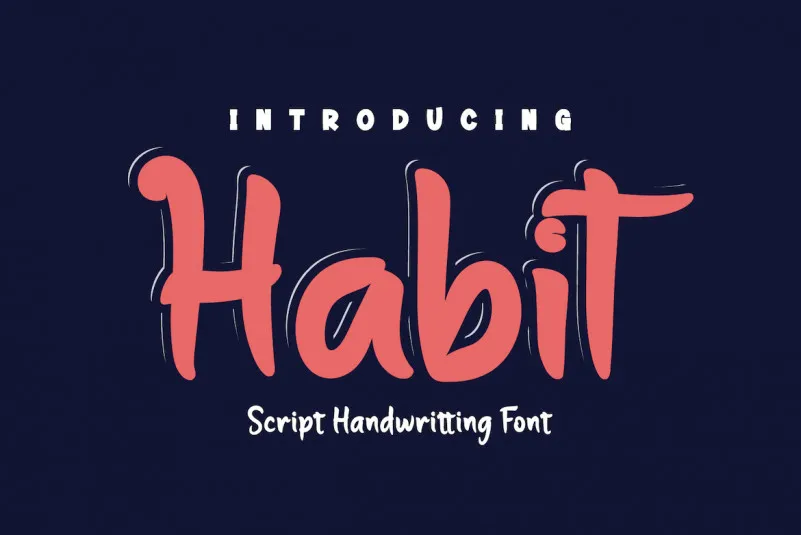
Habit Font é uma tipografia ideal para projetos que exigem uma paleta de cores atraente e um estilo visual único. Desenvolvida com um toque do dedo, ela transmite um equilíbrio perfeito entre elegância e beleza natural, tornando-a uma escolha excepcional tanto para o texto quanto para os títulos de seus projetos arrojados. Suas linhas fluidas e sutis fazem com que a fonte seja atraente em qualquer situação, tornando-a perfeita não apenas para um design original, mas também para criações inovadoras e criativas. Ideal tanto para aplicativos digitais quanto para impressão, a Habit Font é uma excelente opção para aqueles buscando personalizar o seu projeto de forma única e moderna. Sem dúvida, ela se destaca entre as fontes de exibição graças à sua elegância e harmonia natural.